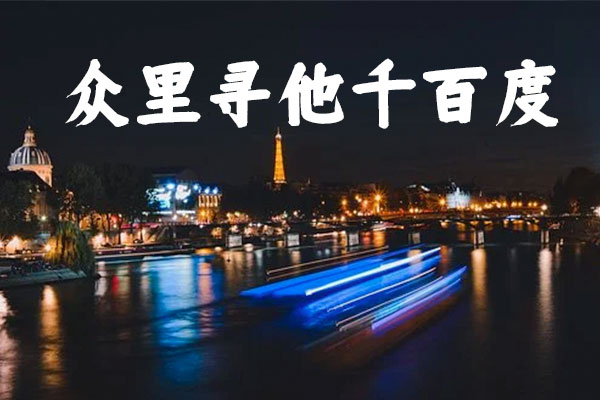
仓耳周珂正大榜书
仓耳周珂正大榜书,这一款引人注目的免费字体,由仓耳字库倾情推出。这款字体的设计理念,借鉴了中国传统书法的精髓,融入了独特的现代审美元素,既体现了传统之美,又不失现代之雅。
仓耳周珂正大榜书的笔画设计极富力度和动感,粗细得当,形态优雅。每一个字形都经过精心雕琢,呈现出独特的艺术韵味。此外,字体家族中的每个成员都拥有统一和谐的轮廓,使得整篇文章的视觉效果更加舒适自然。
这款字体的一大亮点在于其很高的兼容性。仓耳周珂正大榜书支持各种语言和符号,无论是汉字、英文,还是标点符号,都可以信手拈来。这无疑为用户提供了便利,无论在何种场合,都可以轻松应对。